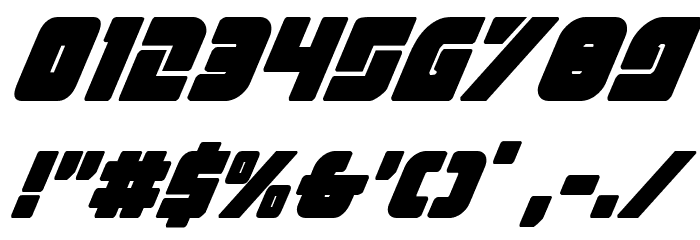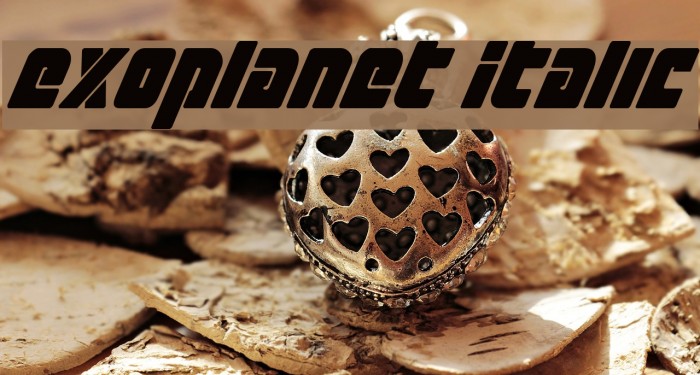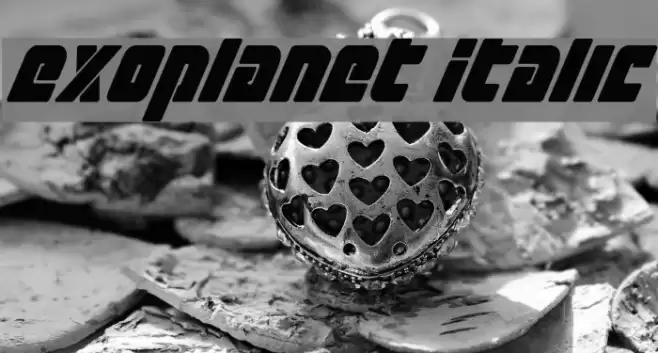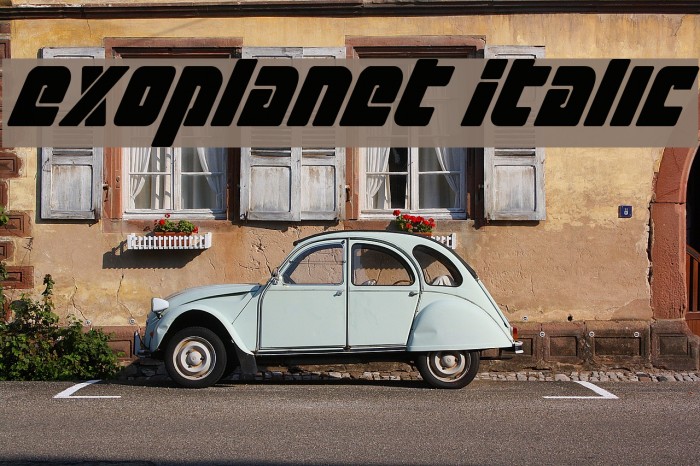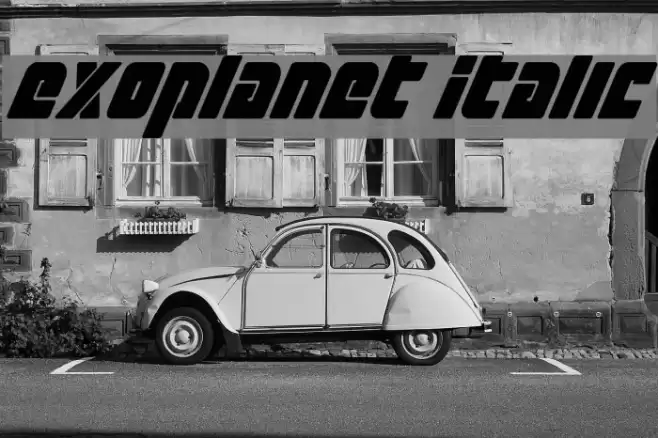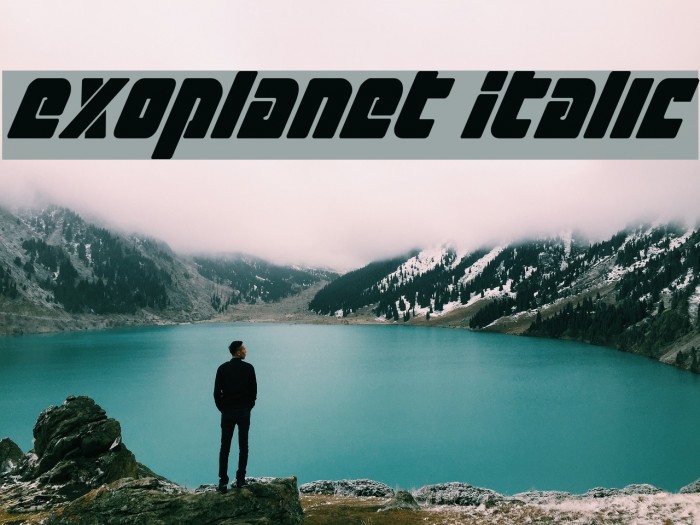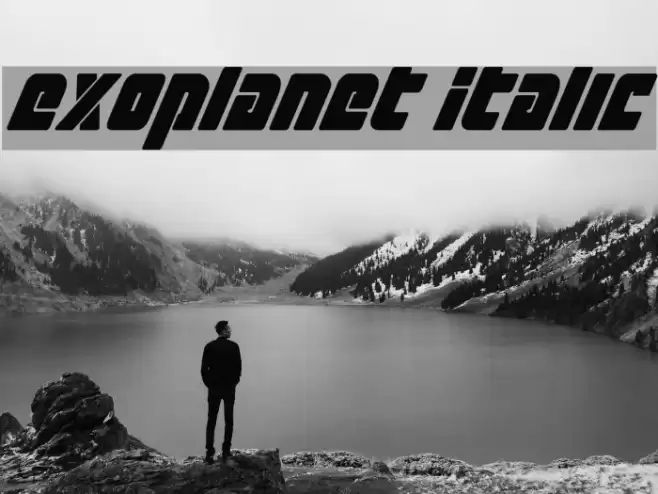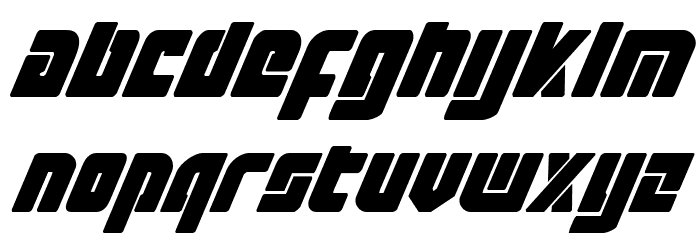
Exoplanet Italic Font
| Progetti proposti | Ideal for sci-fi themed designs, tech company branding, video game titles, and modern advertising campaigns. |
Exoplanet Italic